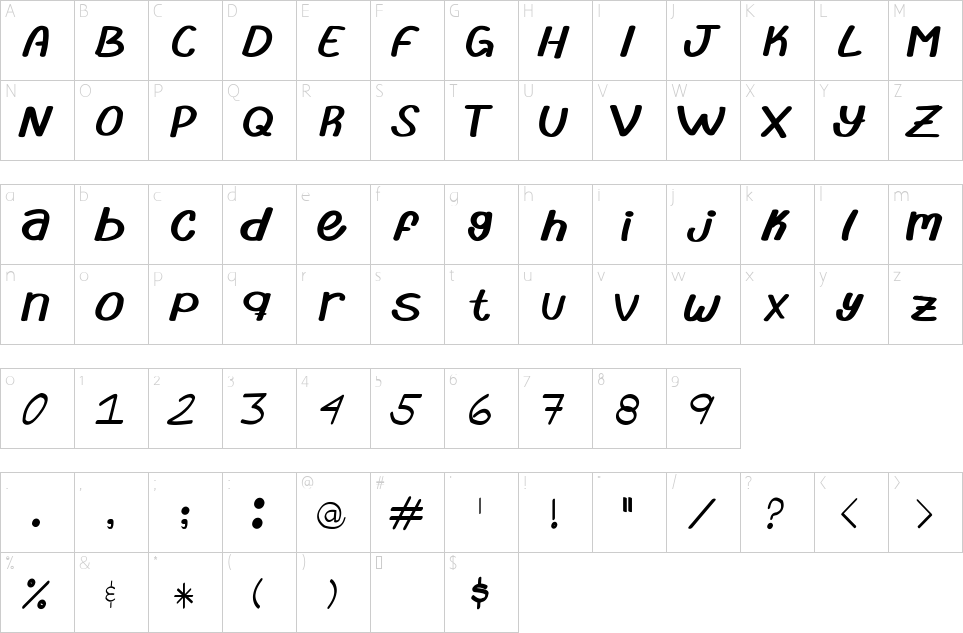
A fonte Abrila é uma opção gratuita e versátil para designers e criativos de todo o mundo. Desenvolvida por Avril Aguilar, esta fonte foi projetada para atender uma ampla variedade de necessidades, desde títulos até textos de corpo, proporcionando um aspecto moderno e elegante. Abrila já foi baixada por 10.641 usuários, evidenciando sua popularidade e qualidade. Se você está procurando por uma fonte gratuita para usar em projetos pessoais ou profissionais, Abrila é uma ótima escolha. Com seu design limpo e sua capacidade de personalização, Abrila pode ajudá-lo a destacar em qualquer projeto.